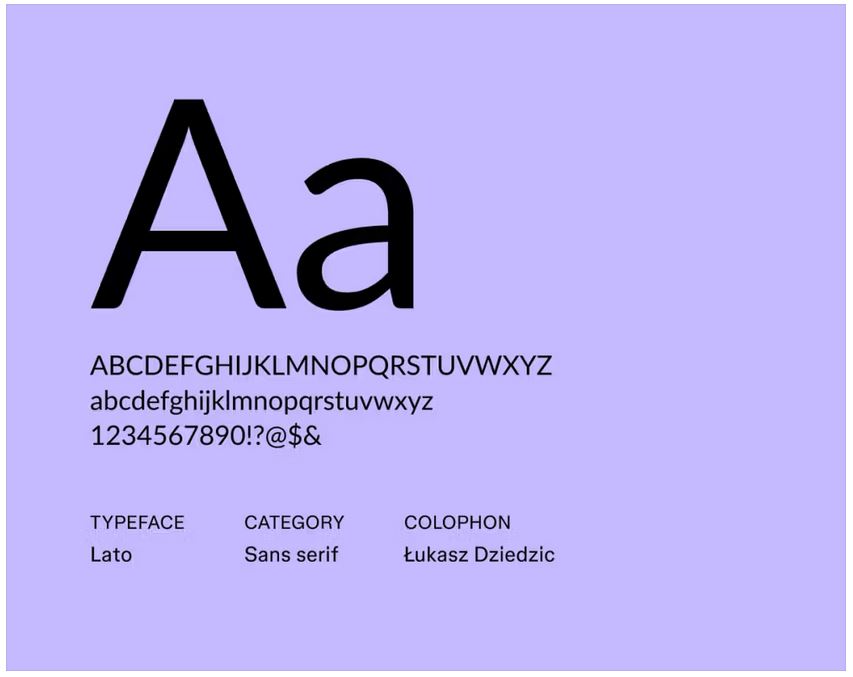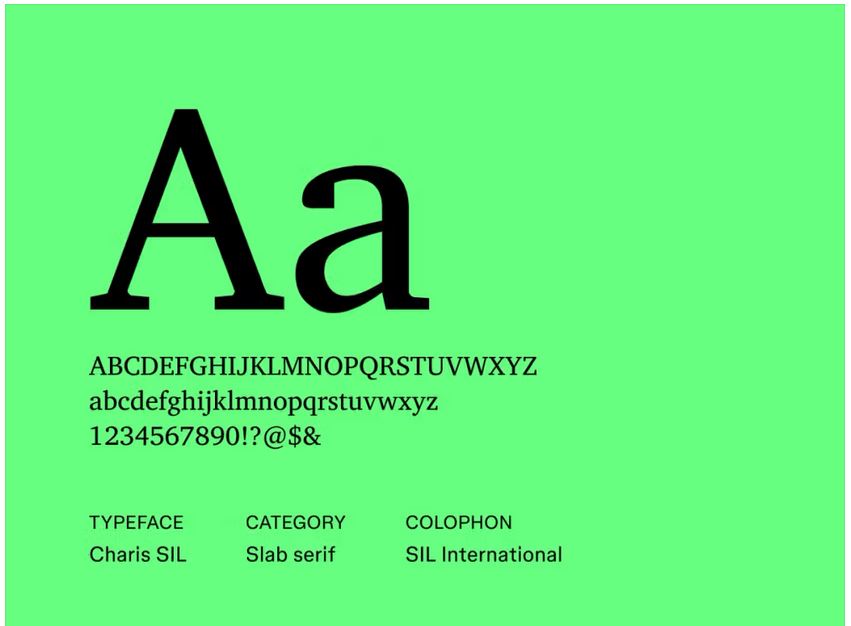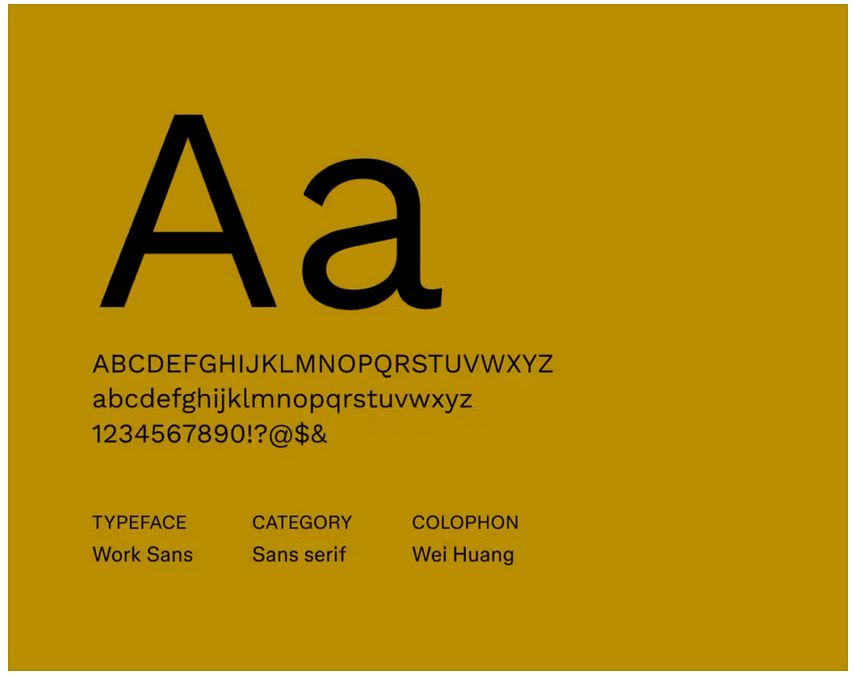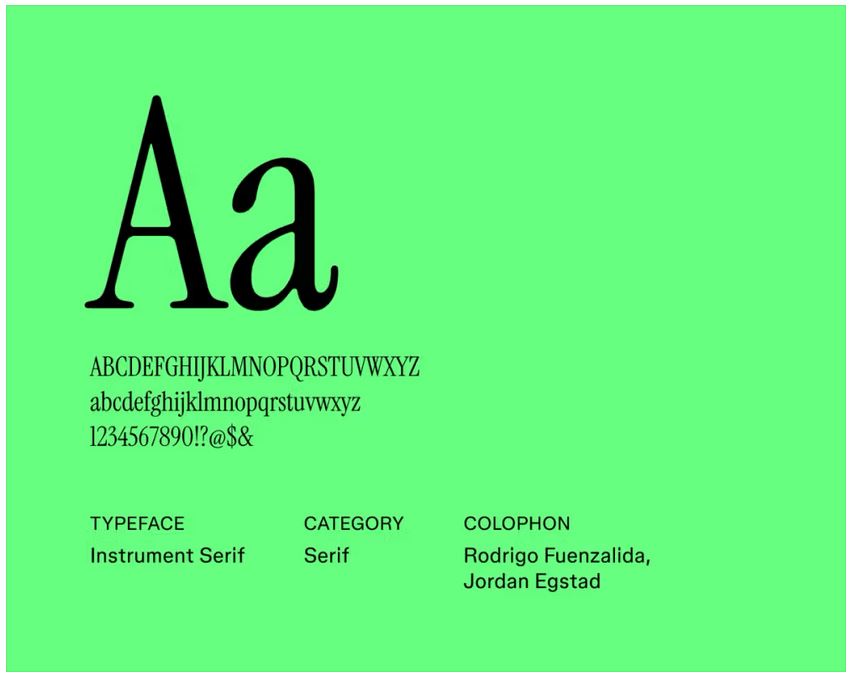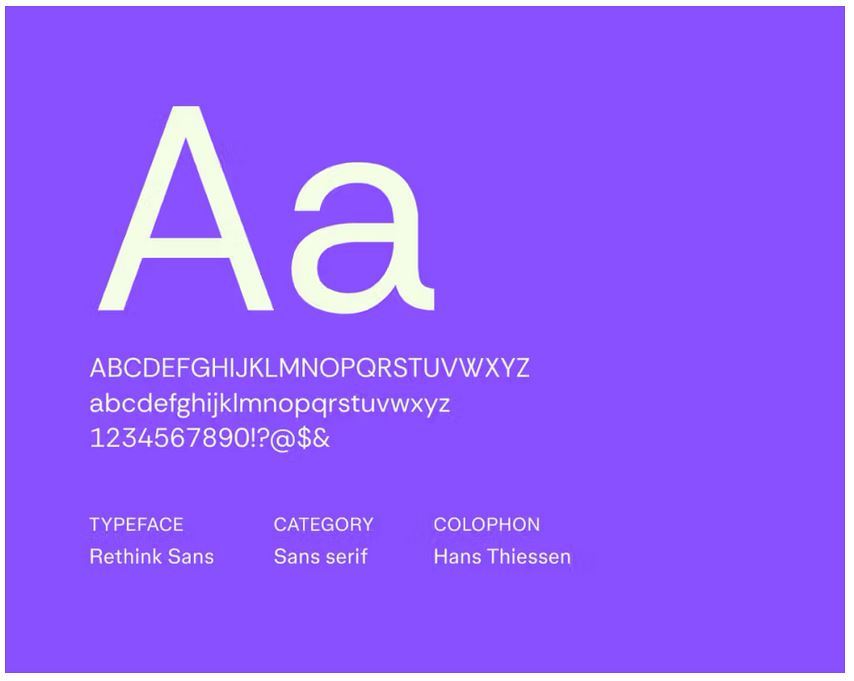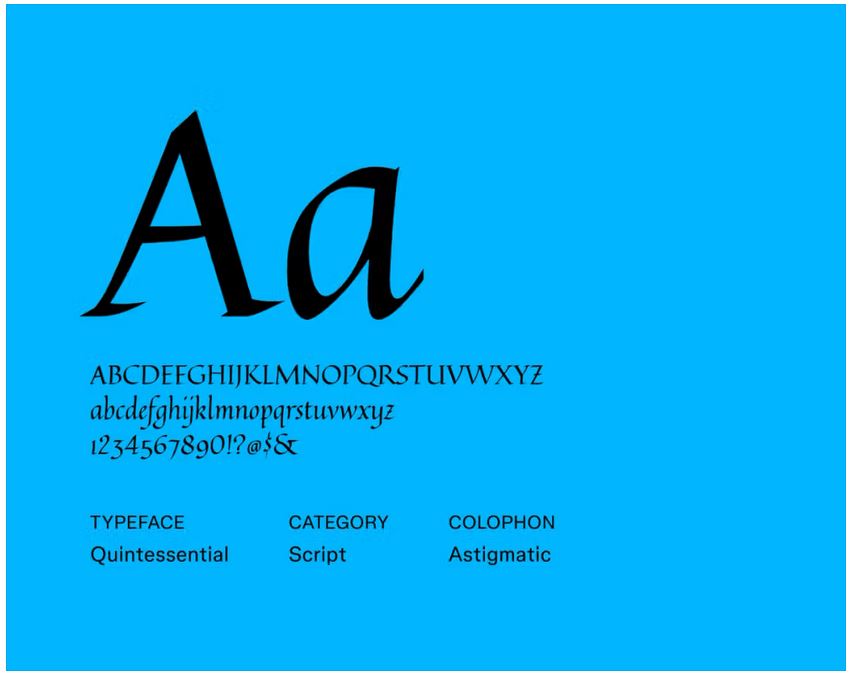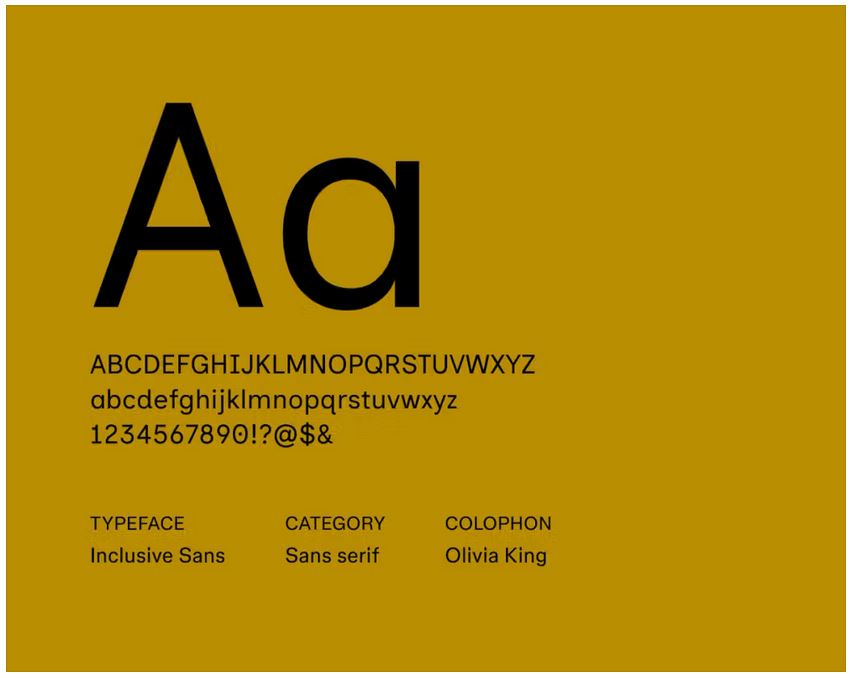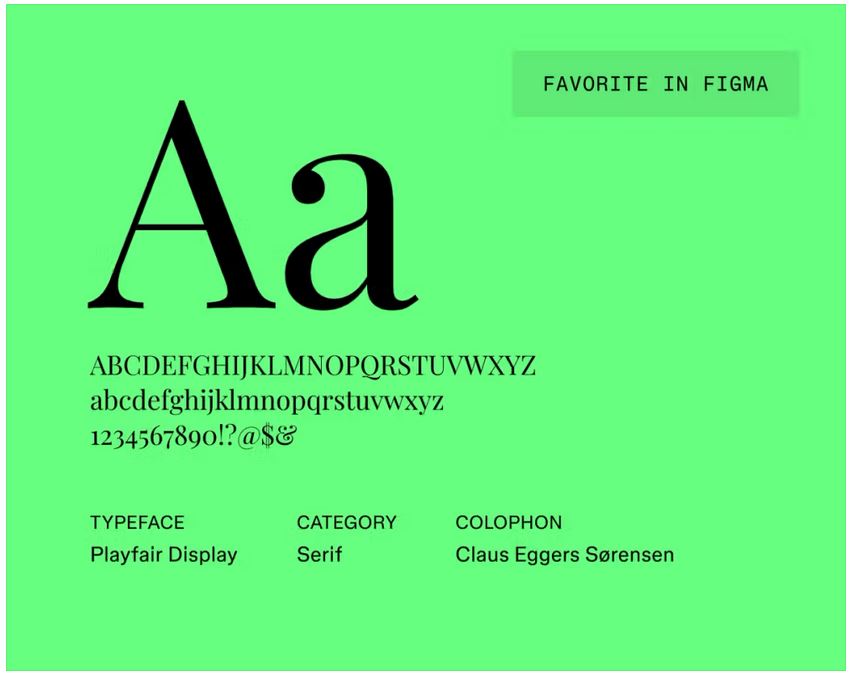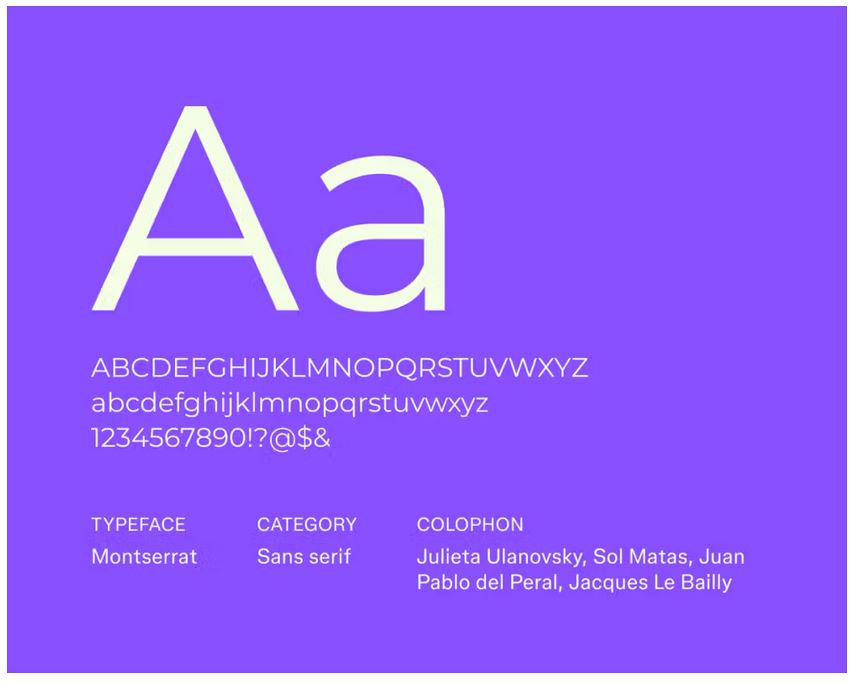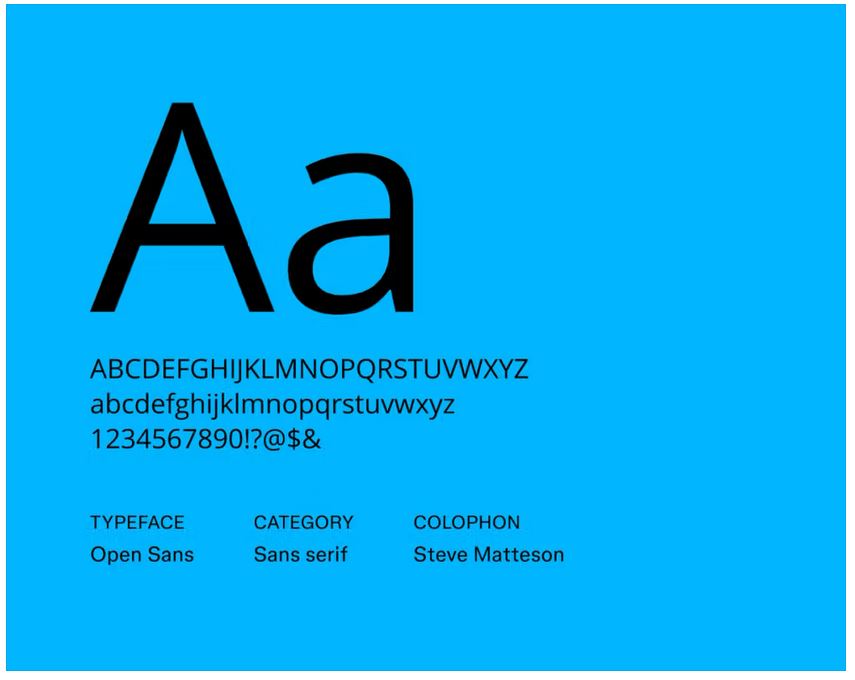
虽然许多人将“现代”和“当代”混为一谈,但现代设计特指19世纪末至20世纪中叶的一场设计运动。若您希望在下一项目中采用这种美学风格,建议选择具有简洁线条、对比鲜明的笔画及细腻衬线的现代字体,以营造时尚前卫的视觉效果。
字体1:Instrument Sans
Instrument Sans 采用简洁现代的设计,注重多功能性。其均衡的比例和中性风格使其适用于专业用途或创意品牌设计。字体的简约设计确保了清晰度和可读性,而现代美学则为整体增添了当代气息。
最佳用途:UI/UX 设计、用户界面、品牌设计及通用正文文本
字体 2:Work Sans
Work Sans 是一款专为屏幕阅读设计的几何无衬线字体。其简洁现代的设计风格使其成为网站和界面中标题与正文字体的理想选择。
适用场景:网页设计、应用界面及极简主义设计
字体 3:Instrument Serif
Instrument Serif 是一种将经典衬线元素与现代美学相结合的字体。它在优雅与可读性之间取得了平衡,是需要呈现精致专业外观的设计的理想选择。
适用场景:编辑设计、长篇内容及书籍
字体 4:Rethink Sans
Rethink Sans 是一款几何无衬线字体,专为现代且亲和力强的设计风格打造。其简洁流畅的线条使其成为科技相关设计或当代品牌标识的理想选择。
适用场景:用户界面、网站、教育材料及包容性设计
字体 5:Quintessential
Quintessential 是一款充满趣味的脚本字体,带有复古的手写风格。它为设计增添了一丝优雅与个性,是现代婚礼材料、艺术项目以及希望传达怀旧氛围的精品品牌的不二之选。
适用场景:邀请函、品牌设计与标志
字体 6:Plus Jakarta Sans
Plus Jakarta Sans 是一款现代几何无衬线字体,兼具亲和力与专业感。它具有极高的灵活性和可读性,非常适合注重可读性的现代设计。
适用场景:UI/UX 设计、移动应用、数字品牌设计及现代网站
字体 7:Inclusive Sans
包容性无衬线字体是一种注重可读性的字体选择,适合所有受众。其开放的字母形态和优化的间距确保在各种设备和尺寸下都能实现包容性设计。
适用场景:网站、应用程序及优先考虑 无障碍访问的项目
字体 8:Playfair Display
Playfair Display 是一款高对比度衬线字体,在大号字体中效果最佳。其精致的细节和优雅的曲线使其成为高端设计和优雅风格的理想选择。
适用场景:标题、标题和编辑设计
字体 9:Montserrat
这款几何无衬线字体灵感源自都市字体设计,将传统元素与现代风格完美融合。蒙特塞拉特(Montserrat)以简洁明快、亲和力强的风格著称,具有极高的适应性,广泛应用于网页设计、印刷设计及品牌视觉识别系统。
适用场景:标题、正文字体、UI/UX设计及品牌视觉设计
字体10:Open Sans
Open Sans 是一款专为屏幕阅读设计的字体,采用中性、易读的设计,适用于网页和印刷设计。它支持多种语言和字重,能够适应各种设计场景。
适用场景:网页设计、应用界面、正文文本及通用设计
字体 11:Lato
Lato 字体以温暖友好的设计风格,确保在不同尺寸和应用场景下都能实现最佳可读性。凭借其现代且亲和的外观,Lato 字体是品牌设计、网页设计及用户界面设计的热门选择。
适用场景:正文文本、网站及应用程序
字体大小 12:Poppins
Poppins 是一款几何无衬线字体,采用现代风格设计。其简洁的线条和均匀的笔画宽度营造出平衡与清晰的视觉效果,而微妙的圆角则增添了一丝温暖与亲和力。
适用场景:标志设计、网页设计、应用程序界面及现代品牌视觉识别
字体 13:Charis SIL
Charis SIL 是一款注重可读性的无衬线字体,即使在小字号打印或显示时,文字也能清晰突出。它非常适合需要中性且功能性强的字体场合。Charis SIL 经过优化,适用于印刷和数字显示,提供多种字重和样式。
最佳用途:正文文本和长篇内容
H2: 字体 14: Domine
Domine 是一款专为数字屏幕设计的易读衬线字体。其坚实、简洁的线条与均衡的比例,赋予文字清晰度与精致感,适用于网站、博客及文档。Domine 是追求现代风格的当代应用的理想选择。
最佳用途:正文文本、博客、标题、正式文档及数字阅读
字体 15:Bodoni Moda
博多尼莫达(Bodoni Moda)对经典的博多尼(Bodoni)衬线字体进行了现代重新诠释。该字体采用高对比度与时尚字形设计,非常适合追求精致外观的当代与高端设计。
适用场景:奢侈品品牌、编辑设计及高端杂志
字体 16:Forum
论坛字体以简洁的线条和平衡的构图带来现代清晰感。它灵感源自古罗马铭文,为设计增添古典与现代的融合感。论坛字体非常适合展示用途或品牌设计,呈现永恒经典的风格。
适用场景:正式邀请函、经典品牌设计、标题、书籍封面、历史主题设计
字体 17:Chonburi
Chonburi 是一款展示型衬线字体,其受泰国设计启发的造型散发着复古气息。这款字体充满活力的个性使其成为现代品牌打造复古、活力与大胆品牌形象的独特选择。
适用场景:标题、标题文字、海报及复古品牌设计
字体 18:Xanh Mono
Xanh Mono 是一款现代无衬线字体,线条简洁,比例协调。它专为展示和阅读设计,适用于各种设计项目。
适用场景: 标志、标题、技术文档和创意品牌设计
字体 19: Corben
Corben 是一款设计活泼的显示字体,适合网页使用。其精致 yet 亲和的设计风格(注意其略微圆润的边缘)使其成为追求非正式但仍保持专业感的项目的理想选择。
最佳用途:网站、标志、标题、在线广告及创意品牌设计
字体 20:Roboto Serif
Roboto Serif 是一款现代、易于阅读的字体,专为提供舒适的屏幕阅读体验而设计。它采用简洁、干净的设计,适用于各种屏幕尺寸。由于它是可变字体,设计师可以获得更大的控制权和灵活性来调整样式。
最佳用途: 响应式网站、应用程序界面和用户体验设计
Font 21: Pridi
Pridi 是一款融合了泰式设计元素与现代排版风格的当代字体。其多用途性使其适用于数字和印刷应用,呈现出一种精致的设计风格,完美平衡了传统与现代极简主义。
适用场景:标题、文化出版物、杂志及现代品牌设计
字体 22:Arapey
阿拉佩的微妙对比与优雅流畅的线条,赋予其精致现代的视觉效果。其优雅柔和的风格,使其非常适合打造高端、经典且充满休闲感的品牌形象。
适用场景:正文文本、标题及高端品牌标识
字体 23:蒂恩
蒂恩(Tienne)是一款专为在线使用设计的现代衬线字体。其经典风格与稳健的比例,为传统衬线字体注入了现代诠释,确保可读性同时保留独特个性。
适用场景:网站、在线品牌设计及博客
字体 24:Manrope
Manrope 是一款无衬线字体,采用简洁、极简主义的几何设计。它在各种尺寸下均具备良好的可读性和灵活性,因此成为数字界面和现代品牌设计中的热门选择。
适用场景:UI 设计、网页设计及现代品牌设计
字体 25: Nunito Sans
Nunito Sans 是一款简洁现代的无衬线字体,适用于多种应用场景。其友好亲切的视觉风格使其非常适合在数字产品中营造积极的用户体验,无论是用于正文文本还是标题。
最佳用途:标题、正文文本、用户界面、网页设计和移动应用
字体 26:Inter
Inter 是一款现代无衬线字体,专为提升数字屏幕上的可读性而设计。其开放的字母形态和优化的可读性使其成为科技项目和专业品牌设计的理想字体选择。
适用场景:用户界面设计、企业或科技品牌设计、应用程序设计以及数字出版物
字体 27: DM Sans
DM Sans 是一款几何无衬线字体,采用低对比度设计,呈现干净专业的视觉效果。其在小字号下的出色可读性,使其成为追求简约亲和品牌形象的现代品牌的理想选择。
适用场景:网站、应用程序及品牌宣传材料
字体 28:Red Hat Display
Red Hat Display 是一款专为展示用途设计的无衬线字体。其强劲有力的字母形态能吸引目光,同时保持视觉吸引力,是希望在保持现代感的同时产生强烈视觉冲击的品牌的不二之选。
适用场景:标题、标题文字及强品牌标识
字体 29:Ubuntu
Ubuntu 是一款现代无衬线字体,注重清晰度和易读性。其人文主义设计确保了出色的可读性,同时保持了现代感。Ubuntu 的多功能性和广泛的语言支持使其成为许多项目的热门选择。
最适合:用户界面设计、网页设计和全球品牌设计
字体 30:Kanit
Kanit 是一款时尚的无衬线字体。其简洁的线条与柔和的曲线营造出未来感与亲和力并存的视觉效果,非常适合现代品牌设计及数字应用。
适用场景:标题、科技品牌及未来主义设计
字体 31:Anonymous Pro
Anonymous Pro 是一款专为编程和科技应用设计的现代等宽字体。它采用精准、易读的字母形态,搭配现代设计风格,适用于极简主义品牌设计。
适用场景:编程界面、现代设计项目及网站
字体 32:IBM Plex Mono
IBM Plex Mono 是一款开源现代字体,属于 IBM Plex 字体家族。IBM 最初设计这款字体是为了在编码时确保可读性,但其出色的可读性使其在设计应用中也非常实用,例如 UI 设计、网站和应用程序。IBM Plex Mono 支持全球语言,使其成为多语言项目的理想选择。
最适合:UI 设计、网站和应用程序
字体 33:Space Mono
Space Mono 是一款现代等宽字体,融合了复古未来主义元素。它常与科幻和科技领域相关联。其统一的外观非常适合展示大段文字。该字体通过几何元素和圆角终端设计,呈现出现代感中带有一丝亲和力。Space Mono 提供多种字重和样式,包括斜体。
适用场景:与科技和科幻相关的文字块
使用现代字体的六个专业技巧
现代字体是营造优雅与当代风格的绝佳选择。遵循以下建议可确保其恰当运用。
. 优先考虑可读性。现代字体通常采用衬线字体,适合标题;然而,无衬线字体因其可读性更佳,更适合正文文本。可通过调整行高和 字距 提升可读性。
. 建立清晰的 视觉层次。以特定方式排列元素可引导观众视线。使用不同粗细和大小的字体建立视觉秩序。
. 保持和谐。主字体应与设计风格和谐统一。测试不同字体搭配,选择最适合您需求的效果。
. 考虑用户需求。选择字体时,用户应是核心关注点。确保所选字体能清晰传达信息,同时兼顾目标受众的阅读体验。
. 善用留白。不要害怕留白(文字周围的负空间)。为字体留出呼吸空间,同时突出关键元素。
. 考虑上下文。由于字体用于杂志、传单、网页或其他媒介,需考虑字体在整体设计中的功能。